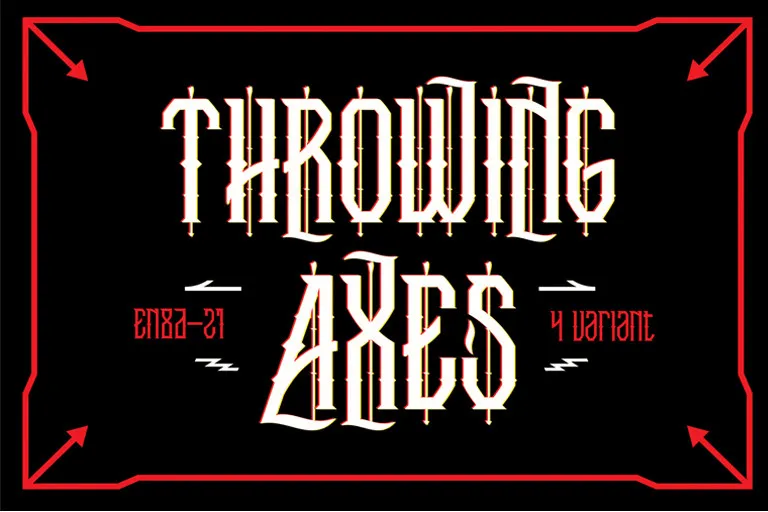
A fonte ‘Throwing Axes Font’ apresenta-se como uma opção única para designers e desenvolvedores que buscam algo inovador e peculiar para suas criações digitais. Especialmente adequada para aplicações criativas onde um visual distintivo seja necessário, esta fonte de categoria Gothic oferece 4 variantes do mesmo conjunto de caracteres — A-Z, a-z, numerais de 1-0 e pontuação básica. Essa elegante seleção de letras foi projetada pela EN86-21 e tem o privilégio de incluir apenas o alfabeto latino. Com sua arquitetura desenhada em estilo gótico moderno, a ‘Throwing Axes Font’ é ideal para criar um contraste visual entre textos formais e gráficos mais criativos. Para quem está sempre à procura de fontes únicas, essa opção se torna ainda mais atraente pela sua singularidade. Seja em sites corporativos, aplicativos ou até mesmo editoriais digitais, essa escolha irá destacar seu design e garantir um visual inovador que mantém o tom sofisticado do estilo gótico. Com uma facilidade de uso impecável e alta qualidade, a ‘Throwing Axes Font’ certamente contribuirá para tornar cada projeto uma verdadeira obra-prima.